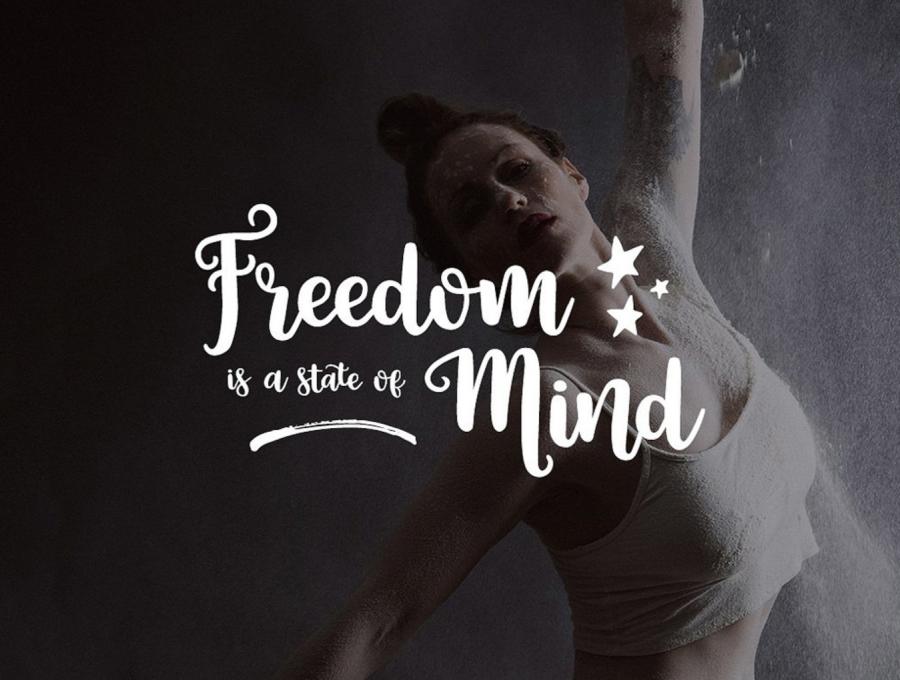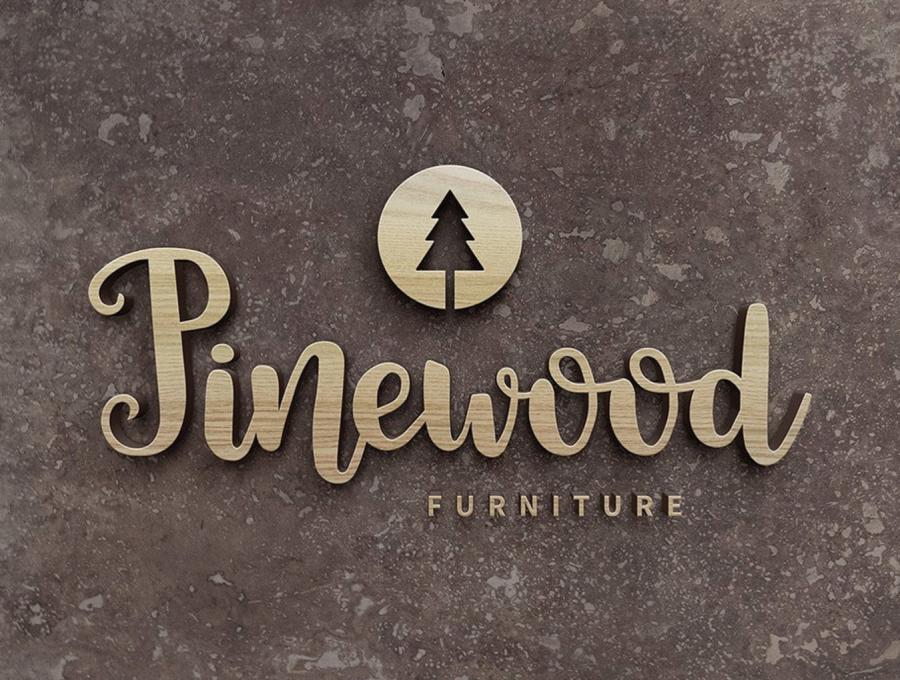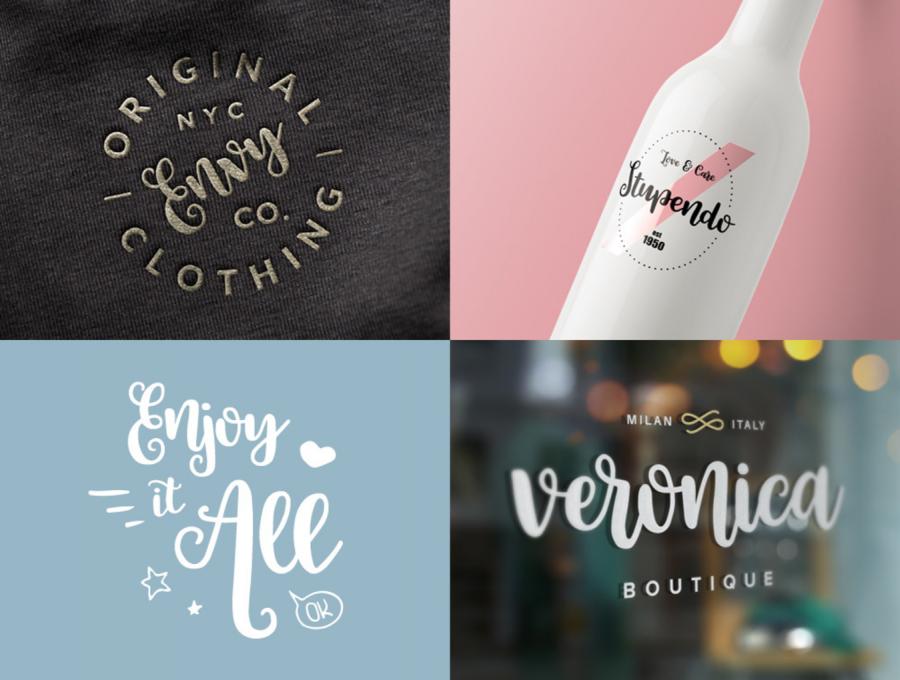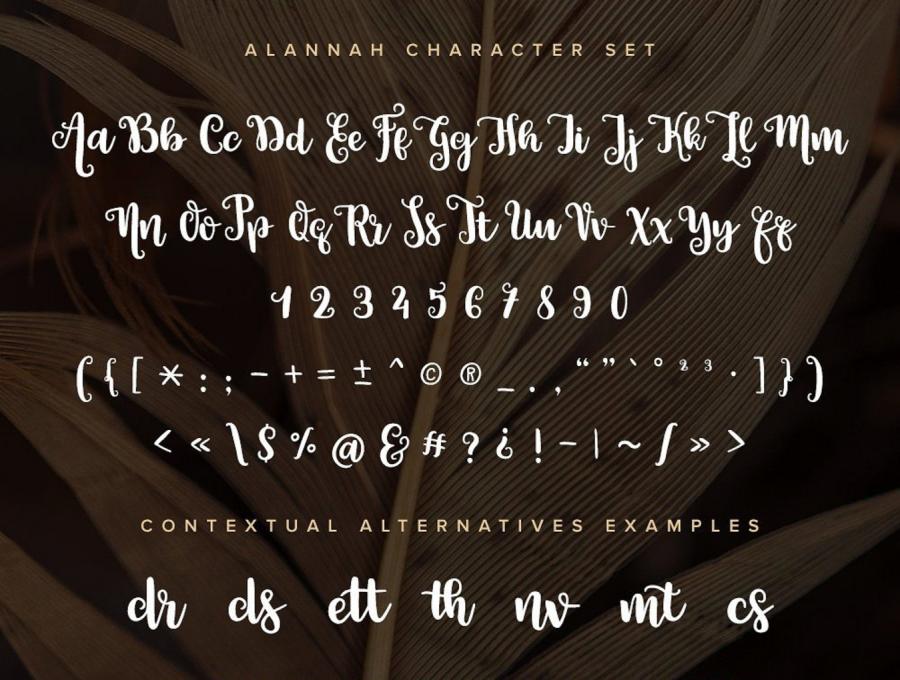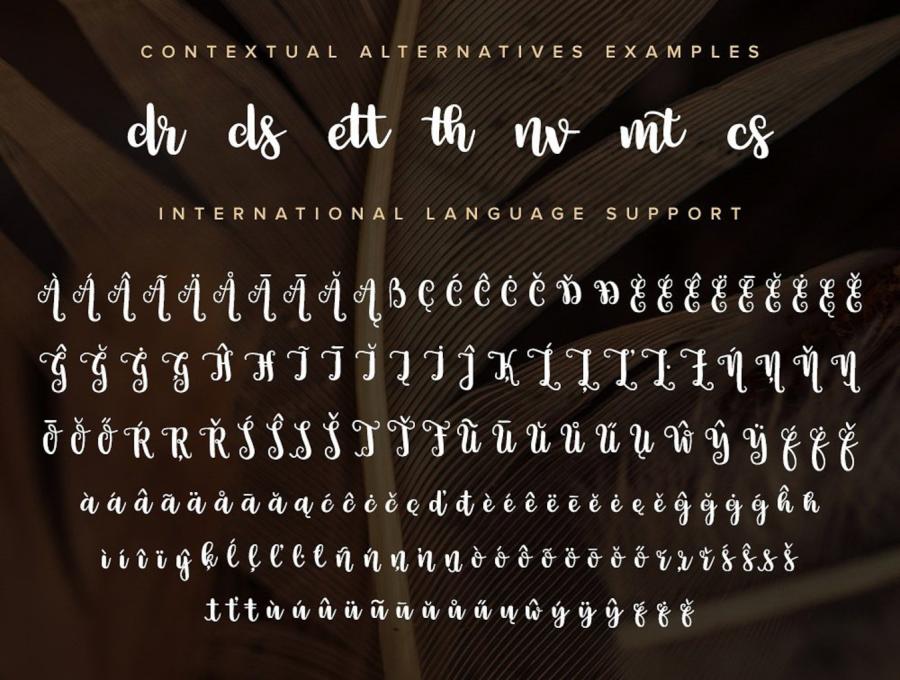
Alannah 英文字体 (Alannah Script Font)
来自Pixelbuddha的第一个字体! 终于向您介绍了与Junik Studio合作的结果,令人激动。 我们的主要目标是给字体带来俏皮快乐的感觉和真正的手写字母的外观。 Alannah可以添加到您的任何设计项目中,与从您的收藏中挑选正确的字体一样简单。 Alannah是一个周到和专业制作的字体,提供广泛的国际语言支持和丰富的Open Type功能,包括各种语境交替和连字。